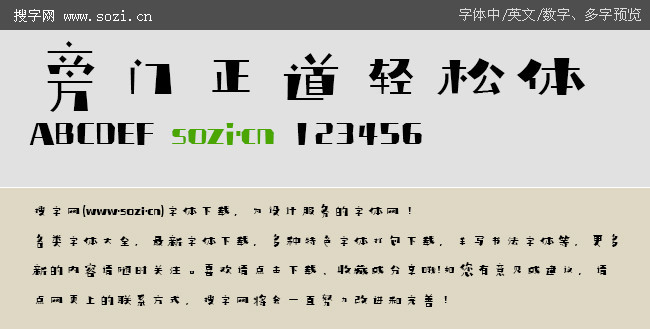
龐門正道輕松體
搜字網(wǎng)給大家提供一款龐門正道輕松體字體中文字體下載,該字體線條粗左粗右細(xì),字形設(shè)計(jì)大方得體,風(fēng)格比較卡通形,趣味十足,字形活潑。適用于大標(biāo)題、包裝設(shè)計(jì)、海報(bào)設(shè)計(jì)等應(yīng)用。